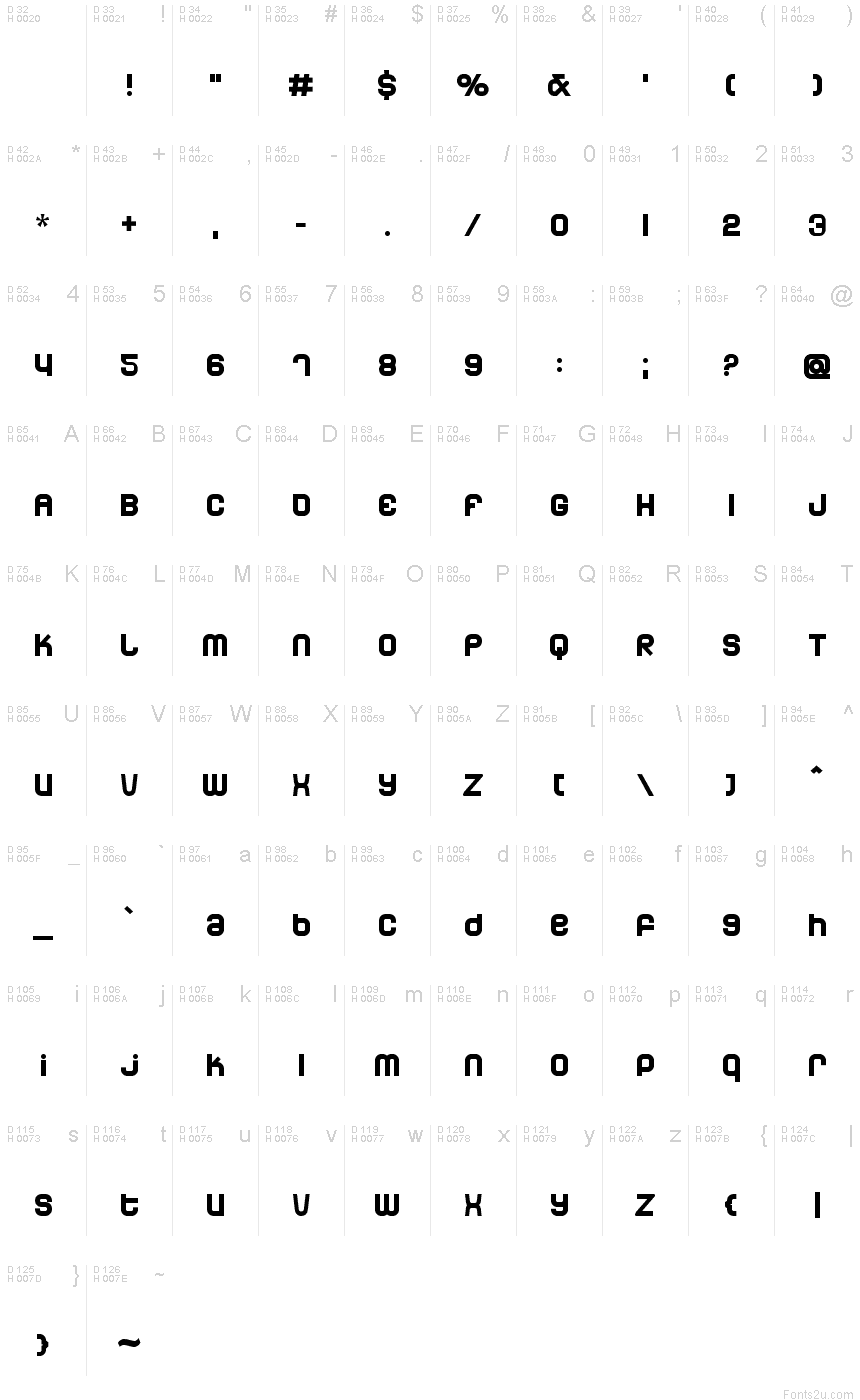
Dunebug od Font a licious Fonts to nowoczesny krój displayowy o śmiałym, tubularnym rytmie, który łączy w sobie klimat tech i zabawę. Zaokrąglone narożniki, kwadratowe światła liter i równomierna grubość kresek nadają każdej literze gładki, plastikowy połysk – jakby tekst został wytłoczony z pojedynczego, błyszczącego paska. Dzięki ciasnemu kerningowi słowa są zwarte i wyraziste, co sprawia, że nagłówki odbierane są bardziej jako jednolita forma graficzna niż zbiór pojedynczych znaków.
Dunebug to świetny darmowy krój, który sprawdzi się w futurystycznym brandingu, plakatach sci-fi, tytułach gier, ulotkach wydarzeń, ekranach powitalnych aplikacji czy wyrazistych logotypach. Geometryczne krzywe błyskawicznie przywodzą na myśl świat cyfrowy, nie sprawiając przy tym wrażenia chłodnych czy klinicznych. W przypadku dłuższych tekstów pomocniczych, Dunebug warto zestawić z czystym, neutralnym krojem bezszeryfowym o lżejszej grubości i mniejszym rozmiarze, aby to masywne pismo główne grało pierwsze skrzypce.